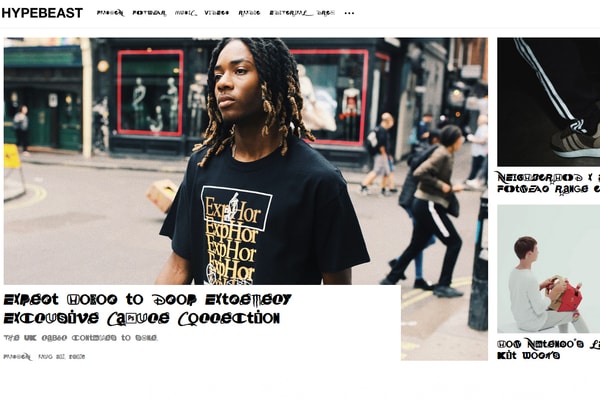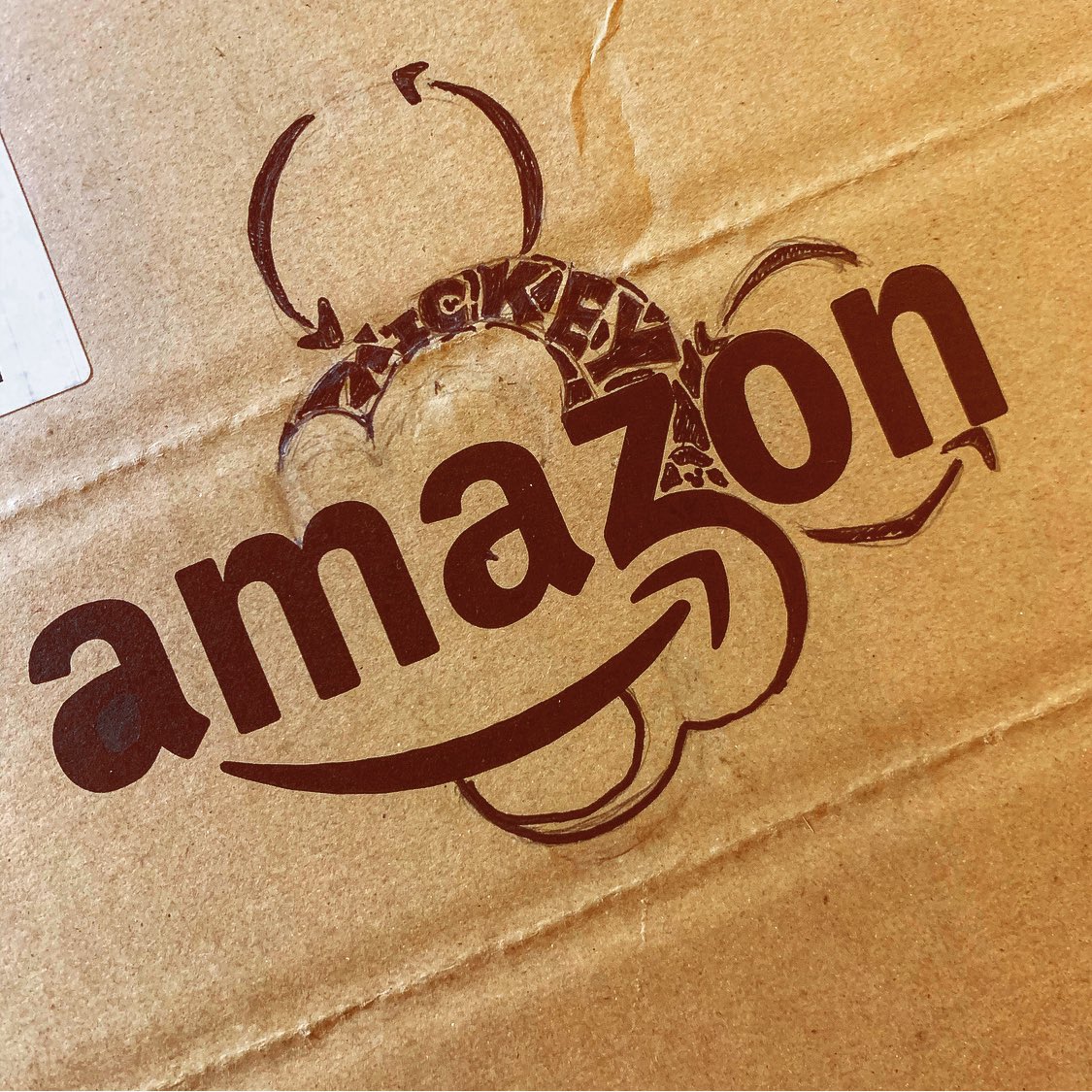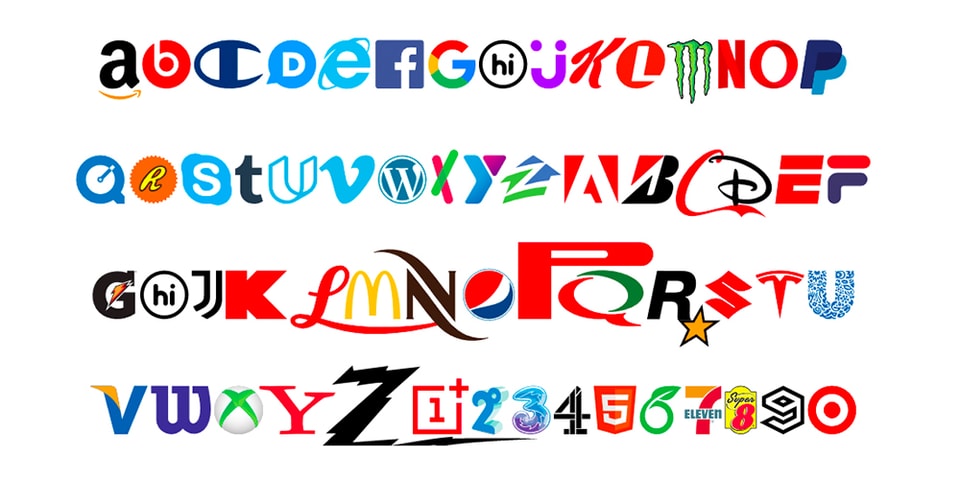
Amazon ロゴ フォント
具体例としてAmazonのロゴを例にご説明します。 今回はロゴのフォントを選ぶ際のコツとおすすめのフォントをご紹介します。 ロゴのフォント選びはWEBデザインやグラフィックデザインとは違い、視認性はや可読性よりはフォントが与える印象を注視して.
Amazon ロゴ フォント. 1 Amazonロゴの由来は? ・ 名前の由来はアマゾン川から ・ Aから始まる名前にも意味がある 2 Amazonロゴマークの矢印の意味は? ・ 矢印がAからZに向かうことでAtoZを意味する ・ 矢印がZをクリックしているように見える 3 Amazonロゴの矢印にはこんな意味も ・ 矢印がスマイルマークに見える. Amazon Amazonjp アマゾン ネットショッピング Finger font Finger logo hand logo フィンガーロゴ ハンドロゴ 指のロゴ 手のロゴ 手 指 ロゴ フィンガーフォント. ・同じフォントのウエイトで区別。 ・別々のフォントを使って区別。 今回は、別々のフォントを使ってロゴを考えました。 一つは個性的なフォントで、もう一つはわりとベーシックなフォントを。そして選んだのは、Google Fontsからも入手できるMonotonとRubik。.
Amazon や McDonald’s など誰もが知る企業ロゴを用いた斬新なフォントが誕生 地位と名声を手に入れた飲食、IT、ファッションといったビッグ. は、Amazon が事前に承認した方法による以下のロゴ (「Amazon マーク」) の使用に適用されます。本ガイドラインで使用される「Amazon」とは、Amazoncom, Inc およびその関連会社を意味し、「ライセンシー」とは Amazon マークを使用して. の場合は例外です。(eg wwwamazoncojp)なお、文字商標のフォントは以下を推奨します。 欧文フォント: Verdana 和文フォント: MS P ゴシック (2) 商標の右上にTMや(R)マークをつける必要はありません。 (3) Amazonロゴを文章の一部として使用してはなりません。.
正解は 視覚デザイン研究所 というフォントベンダーの「ロゴ丸 r」です。 はい、知らないですよね。 ちなみに回答者は 「マツコの知らない世界」の「フォントの世界」 にご出演された須藤雄生さん(写真右)と、ヤフーのデザイナー 田島佳穂さん(左)。 1問目からご両名とも正解ならず。. 最も人気のある Amazon ロゴ フォント 企業 サイト風ロゴジェネレーター Youtube Amazon Twitter. Tower logo maker タワーロゴメーカー。you can make like a tower records logo タワーレコード(タワレコ)風のロゴが作れます。.
驚くばかり Amazon ロゴ フォント フリー. Webサービス Amazoncojpアソシエイト Supported by 楽天ウェブサービス Webサービス by Yahoo!. そんなamazonのロゴですが、サイト上のフォントでロゴを再現しているのを見かけたので、ついついご紹介。これ、ちゃんとしたテキスト文字なのでコピペできます。 ↓ am͜a͉zon am͜a͉zon.
Amazonロゴ下方にある矢印。これにはある意味が込められています。 00年に制定された Amazon のロゴは、”amazoncom”(amazon 部はボールド体)の黒いサンセリフの文字に、a から z に向かって下向きの弧を描くオレンジ色の矢印が重ねられたもの。. 驚くばかり Amazon ロゴ フォント フリー. アマゾン風ロゴを作ってくれるジェネレータ。 こうして見ると、ミシシッピって結構特徴的なスペルなんですね。 amazon風のロゴを簡単に作れる「amazon logo maker」.
Images Logos Amazonが提供するウェブサービスのロゴをダウンロードできます。ネットショッピングのAmazonはもちろん、KindleやAWS(Amazon Web Service)のロゴも揃っています。. Am͜a͉zon Amazonロゴ下方にある矢印。これにはある意味が込められています。 00年に制定された Amazon のロゴは、”amazoncom”(amazon 部はボールド体)の黒いサンセリフの文字に、a から z に向かって下向きの弧を描くオレンジ色の矢印が重ねられたもの。. このロゴは、以前のロゴを基にしたTurner Duckworthによる再デザインであり、レタリングはおそらくカスタマイズされたものです。 以前のロゴ()に使われているフォントはOfficina Sansだと分かっており、こちらは利用可能です。「Amazon」にはOfficina Sans.